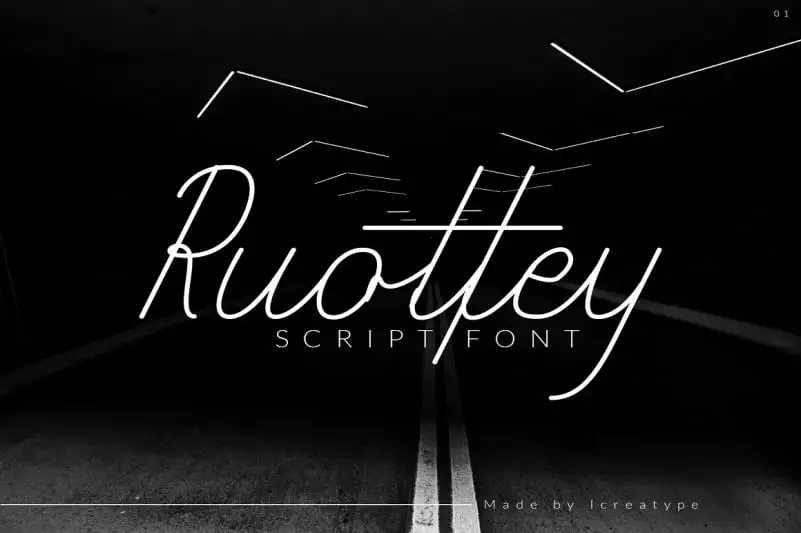
Ruottey Script Font – Download Grátis
A fonte Ruottey Script é uma escolha perfeita para quem busca um estilo elegante e sofisticado em seus projetos digitais, seja eles assinaturas, logotipos ou mensagens importantes. Conhecida por sua fluida elegância e detalhes cuidadosamente pensados, esta fonte é ideal para criar um impacto visual imediato. Desenvolvida pelo designer Icreatype, a Ruottey Script oferece uma maneira única de expressar o seu sinal ou marca. Seu design original e único, combinado com traços delicadamente fluidos, cria um texto que se destaca em qualquer ambiente de design gráfico. A fonte é perfeita para quem busca adicionar um toque atraente à sua identidade visual digital. Ainda mais, o uso desta fonte permite aos usuários expressar sua criatividade de maneira única e personalizada sem comprometer a legibilidade necessária em um ambiente digital. Com seu design cuidadosamente pensado e a funcionalidade completa do Icreatype, a Ruottey Script é uma excelente escolha para designers digitais buscando complementar seus projetos com algo que vai além da simples beleza visual.